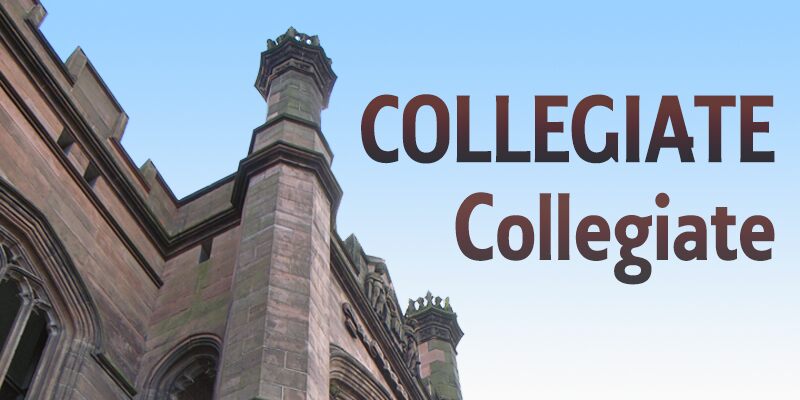
خط Collegiate من K-Type هو خط مجاني بلا زوائد (Sans Serif) يحمل في طياته الهيبة الهادئة للوحات المدارس التقليدية. استوحي الخط من الحروف الموجودة حول فسيفساء مدرسة ليفربول الجامعية (Liverpool Collegiate School)، ويتميز بضربات قوية ومتوازنة مع زوايا مستديرة بلطف تمنحه صلابة دون أن يبدو ضخمًا. الانطباع العام هو طابع أكاديمي يسهل الوصول إليه، يشبه الحروف المرسومة على أبواب قاعات المحاضرات القديمة، ولكن بنسخة رقمية نظيفة.
مع خط Collegiate، ستحصل على نبرة مؤسسية رصينة ومناسبة تمامًا لهوية الجامعات، ومشاريع التراث، وأغلفة الكتب، والشهادات، ومواد الخريجين، وملصقات الحرم الجامعي. بفضل إيقاعه القوي وأشكاله السخية، يظل هذا الخط المجاني مقروءًا من مسافات بعيدة، مما يجعله خيارًا طبيعيًا للافتات واللافتات الإعلانية. نسّق Collegiate مع خط هندسي خفيف للعناوين الفرعية، واترك Collegiate يتولى مهمة الأسماء والعناوين وشعارات الكلمات بأحجام أكبر.